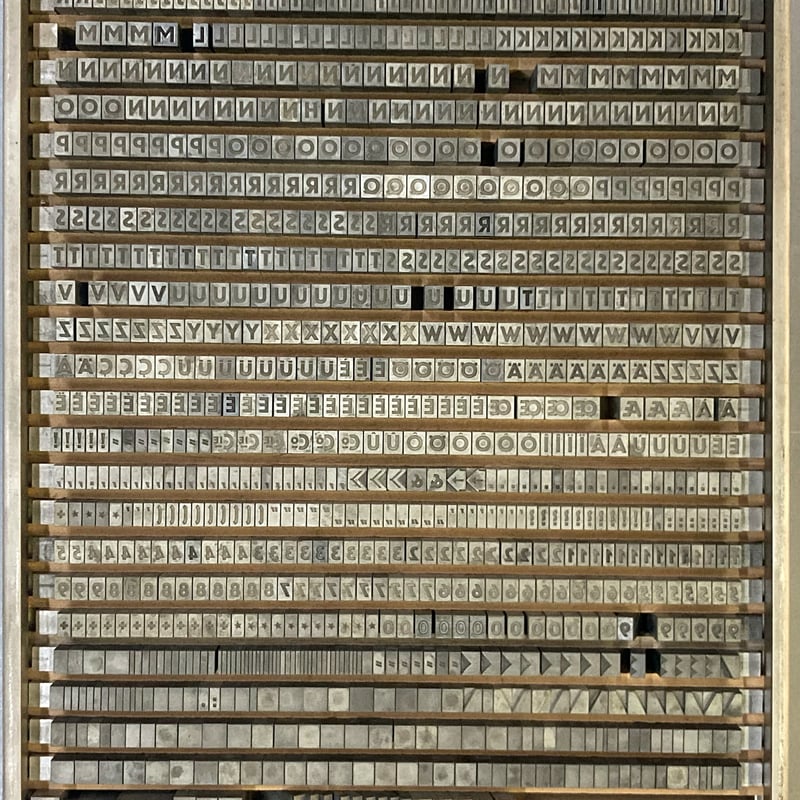
Lucina
Grösse: 20 pt
Druckmuster mit Text «Lucina est l’une des quatre polices en complément de la famille Erbar-Grotesk»
Klassifizierung
Display, Sans Serif
Design
Jakob Erbar
Jahr
1926
Schriftgiesserei
Ludwig & Mayer
Eine invertierte Variante der Erbar-Grotesk, in Grossbuchstaben, mit Rahmenelementen und alternativem S.
Zeichen
ABCDEFGHIJKLMNOPQRSTUVWXYZ0123456789!&()*+,-.:;?ÀÄÆÇÈÉÊËÎÏÔÖÙÛÜŒ’“„
Grossbuchstaben
A-Z
Kleinbuchstaben
nicht vorhanden
Zahlen
0-9
Sonderzeichen
! & ( ) * + , - . : ; ? À Ä Æ Ç È É Ê Ë Î Ï Ô Ö Ù Û Ü Œ ’ “ „